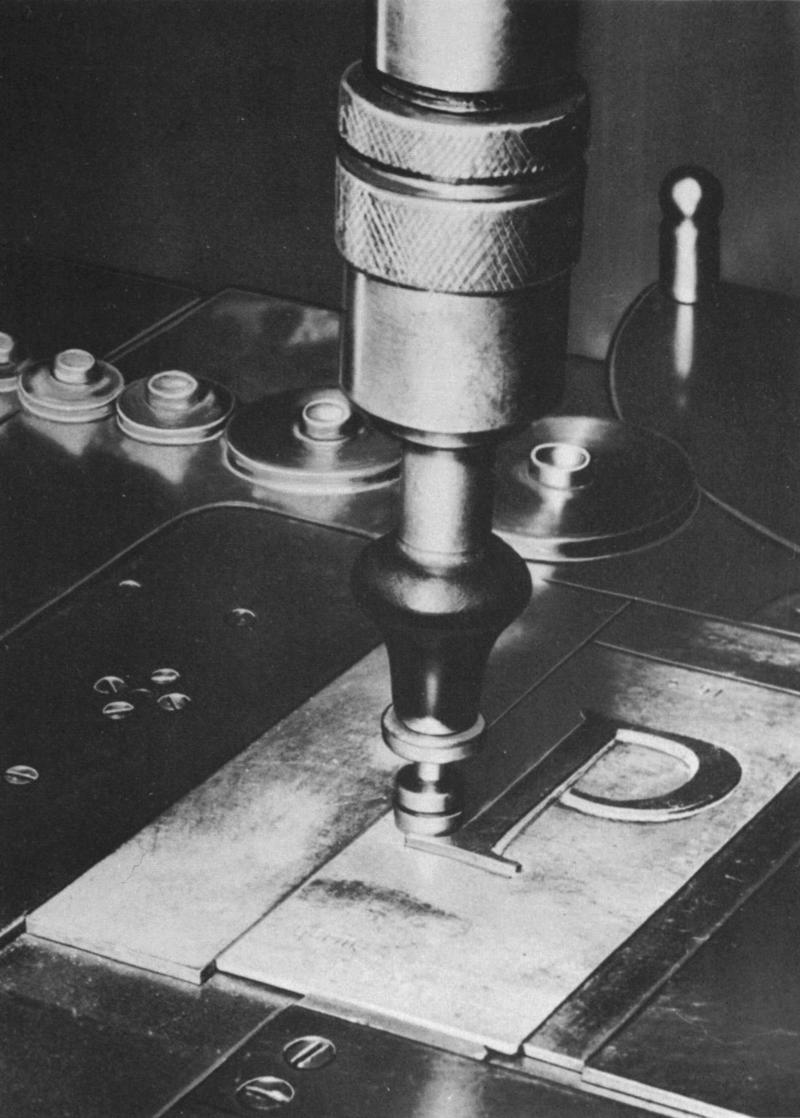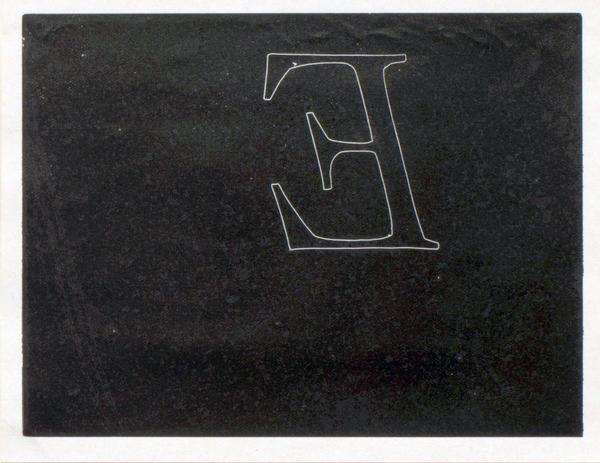
Maschinenstempelschnitt – Schablonen seitenrichtig?
In Abbildungen von Pantographenfräsen für den Stempelschnitt sehe ich immer wieder seitenrichtige Schablonen. Mein Verständnis der Technik ist, dass die Schablone über einen Pantographen abgetastet und verkleinert in den Stempel geschnitten (eigentlich gefräst) wird. Allerdings sind Patrizen immer seitenverkehrt. Wie kommt es, dass die Schablonen seitenrichtig sind?
Mögliche Erklärungen, die mir bisher eingefallen sind:
1. Die Abbildungen sind gespiegelt. Denkbar, aber eigentlich nicht in mittlerweile 3 verschiedenen Fällen. Dummerweise ist auf keinem der Bilder ein Element, an dem man das überprüfen könnte.
2. Die Pantographenfräsen haben nicht nur verkleinert, sondern auch gespiegelt. Allerdings erschließt sich mir der Sinn dabei nicht. Ein einfacher Pantograph spiegelt nicht und jede Komplikation kostet Genauigkeit.
3. Es ist gar nicht Stempelschnitt, sondern Matrizenbohren. Kann nicht sein, da die Schablone erhaben ist.
4. ich stehe auf dem Schlauch (momentaner Favorit)
Hier noch ein Beispiel:
unfundierter zwischenruf: was, wenn seitenrichtig die vorlagen für – beispielsweise – mono- oder linotypematrizen gefräst worden wären?
Hm, es wurden schon auch Matrizen gefräst, aber da sehen die Schablonen anders aus: Die Schrift ist vertieft und nicht erhaben.
Übrigens wurden jedenfalls für Linotype-Matrizen Stahlstempel gefräst und die Matrizen davon gefertigt. Jede Matrize zu fräsen hätte zu lange gedauert. Und wenn man in der Produktion einen Stempel verschlissen hatte, konnte man druch das Schablonenfräsen identische Stempel nachproduzieren, was von Hand nie funktioniert hätte.
Dein Bild zeigt einen Pendelpantographen, bei dem die Schablone immer mit seitenrichtigem Bild befestigt ist. Beim Matrizenbohren ist die Schablone ebenfalls seitenrichtig.
Jetzt verstehe ich's. Diese Bauform spiegelt das Ergebnis immer und daher braucht man eine seitenrichtige Schablone. Danke!
Wenn die Schablone fürs Matrizenbohren ebenfalls seitenrichtig ist (worin ich Dir recht geben würde) muss das Matrizenbohren dann aber eigentlich mit einem Scherenpantographen stattfinden, denn die Matrize ist ja seitenrichtig.
Hier der Abzug einer Matrizenbohrschablone, der seitenverkehrt ist, weshalb die Schablone seitenrichtig gewesen sein muss (mir ist jetzt offiziell schwindlig)
Generell sei gesagt, das es diverse Methoden zur Matrizen Herstellung gab und diese auch bunt gemischt praktiziert worden sind. Geprägte, galvanische Kopien, gebohrte, aus Stahl, Kupfer, Messing, Bronze, Nickel ... bei den Schablonen gab es daher ja auch erhabene, eingetiefte und diese dann sowohl seitenrichtig als auch verkehrt.